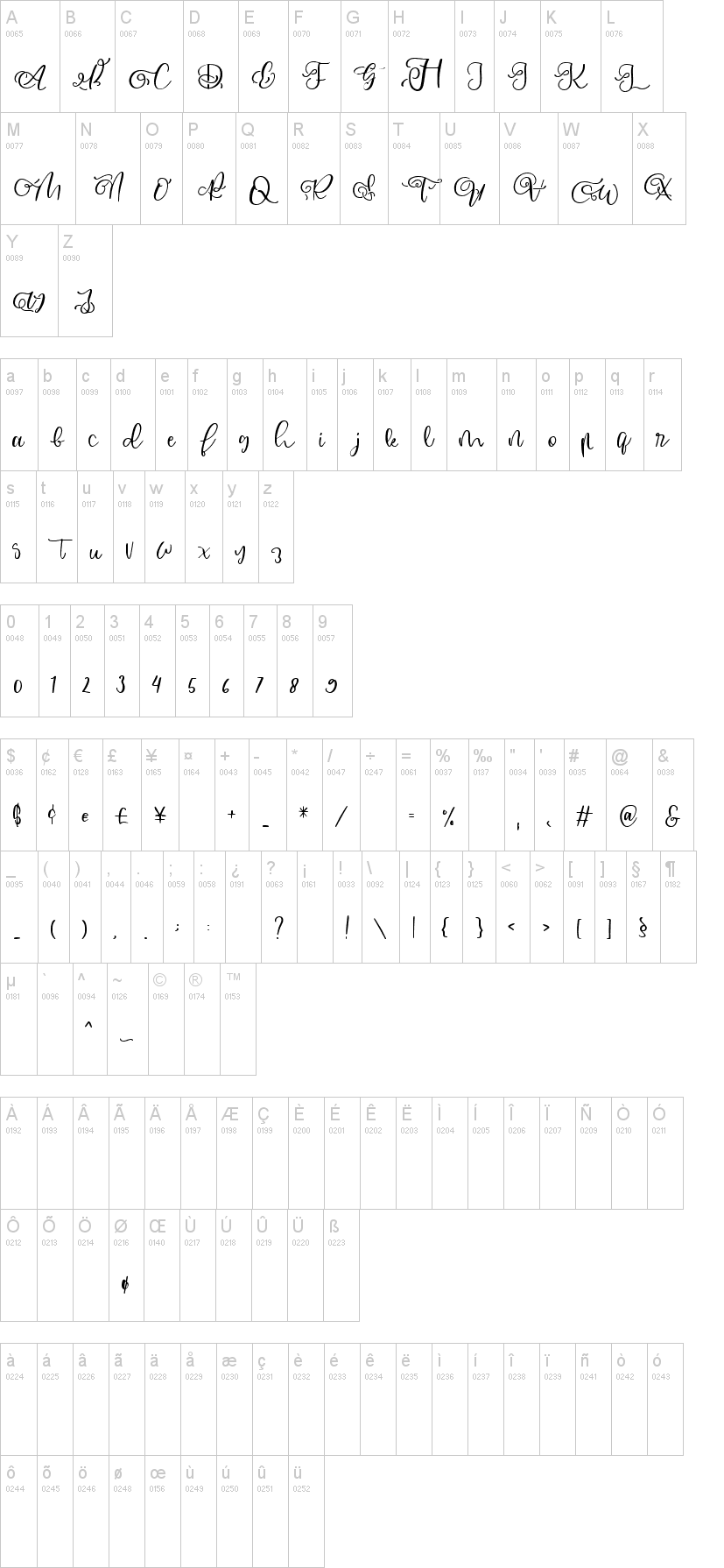
Sally
Sally 字体是一款由 Fontfabric 公司推出的手写体字体,它具有流畅的线条、温柔的曲线和舒适的感觉,能够营造出温暖的氛围。Sally 字体的字母和数字具有自然的曲线,使得它非常适合用于设计海报、商标、宣传单等排版项目。此外,它还非常适合用于配合图片、文字等做出有趣的排版效果。
Sally是一款非常不错的手写艺术字体,具有很好的视觉感,适合于文化类的宣传设计、商业类品牌的广告和产品包装设计以及个性化文字排版等较多场景。
Sally字符映射图